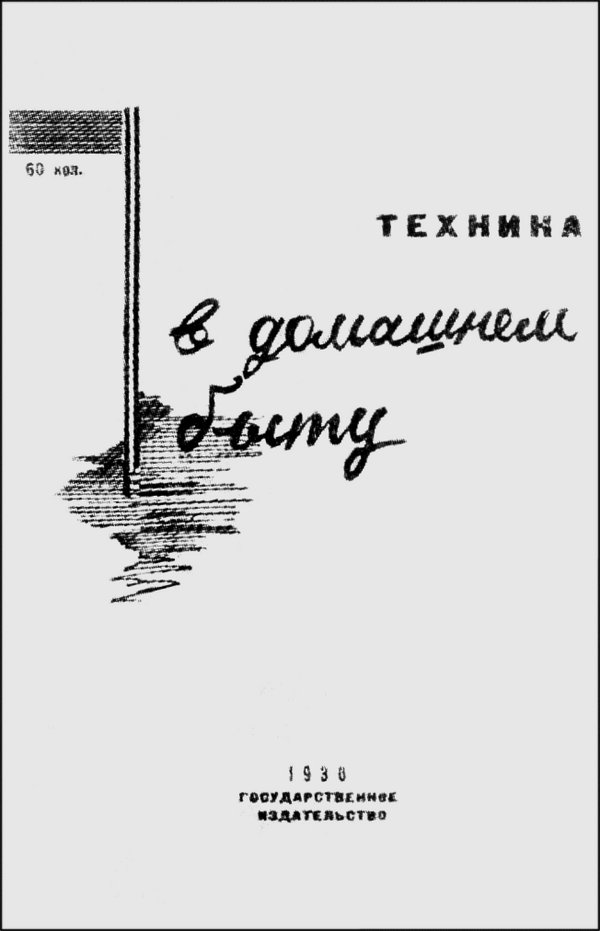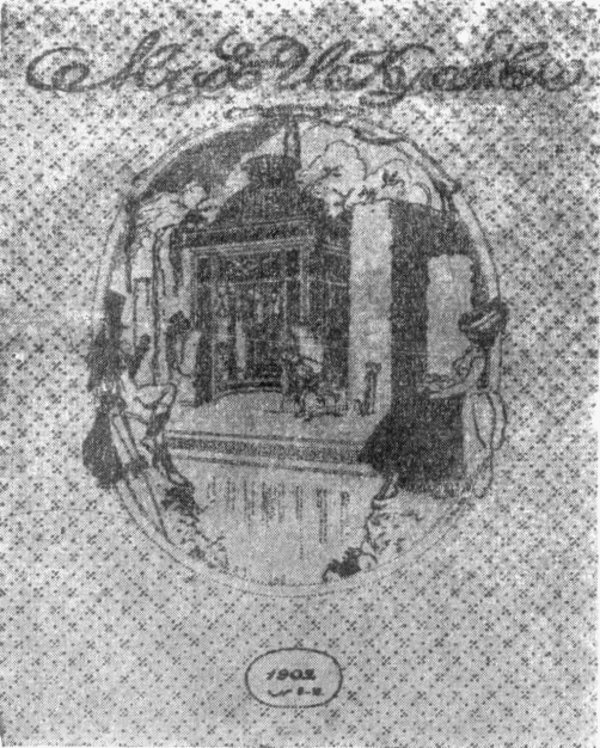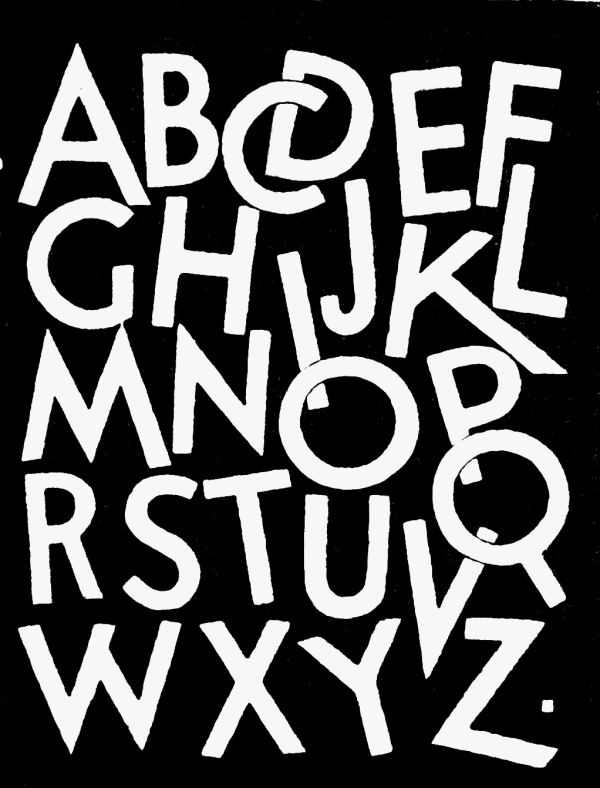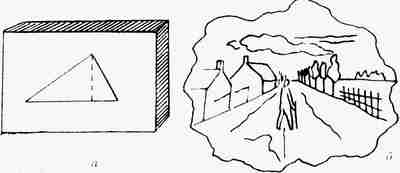
Шрифт и иллюстрация существуют рядом, на одной и той же странице, они находятся в теснейшей связи между собой, но, к сожалению; законы их взаимодействия редко принимаются во внимание. В. А. Фаворский предложил разделение всех букв на четыре группы:
Рис. 391 Разная ширина букв |
Рис. 392 "Рукописный" шрифт |
Всякая буква, взятая равномерным тонким штрихом (рис. 394, а), как бы теряет свою объемность. В буквах этого вида будет сильно сказываться движение по строке. Наиболее чистый вид такого шрифта — рукописный, особенно, если он написан карандашом. В одномерной букве основной вертикальный штрих (штамб) становится только частью контура, не отличающейся от других его частей.
Если приблизить дуги букв к полукружиям (б), усилив в то же время штамб, то этот штамб приобретает значение объемной оси, от которой зависят дуги. Буква приобретает как бы "позвоночный столб", становится предметной, объемной.
Если придать штамбу большую цветность (в), то он создаст впечатление глубины, и получится третий вид буквы — пространственный.
Крупнее: 600x931, 43kb Рис. 393 Неудачное сочетание наборного и рукописного шрифтов на обложке |
Четвертым видом буквы является жирная буква плакатного типа (г). Такая буква вследствие своей перегруженности цветом приобретает характер двухмерной цветовой поверхности.
Как бы ни относиться к предложенным условным наименованиям типов букв, следует признать, что распределение шрифтов по таким типам вполне возможно.
Из существующих типографских шрифтов к первому типу может быть отнесен рояль-гротеск (а также рукописный), ко второму — латинский, к третьему — альдине и к четвертому — дубовый.
Большая часть иллюстраций соответствует какому-нибудь одному из рассмотренных типов букв. Линейный орнамент, например, соответствует одномерной букве, предметная иллюстрация — объемной; иллюстрация пространственная, основанная на цвете и тоне, соответствует пространственной букве; четвертому типу буквы соответствует иллюстрация, выполненная в черно-белой манере.
И буквы, и иллюстрации входят одновременно в книгу и должны быть объединены. Связь между ними может быть двоякая — непосредственная и посредственная.
Если все элементы, входящие в книгу, близки между собой (например, профильные,объемные и двухмерно-цветовые), связь будет непосредственной. Если же в книгу входят разные элементы (например, профильные и пространственные), то они не могут быть объединены непосредственно, а лишь посредством подчинения одного другому или подчинения нескольких.
Рис. 394 Различные типы букв (по Фаворскому) а - одномерно-профильная; б - объемная; в - проостранственная; г - двухмерно-цветовая |
Рис. 395 Схема связи рисунка со шрифтом |
Все типы букв могут быть соединены в две группы. В одну входят буквы трофильная, объемная и двухмерно-цветовая, в другую — пространственная.
Достичь непосредственной связи между обеими группами трудно. Так, например, не всегда возможно оединение двухмерно-цветовой буквы (дубовой) с пространственной (английской или альдине).
Но и в пределах одной группы связь относительна. Она легко достижима, например, между профильной и двухмерно-цветовой буквами (рояль-гротеск и дубовый или гермес), но сложна при объединении двухмерно-цветовой с объемной.
Простейшим случаем непосредственной связи между иллюстрацией и буквой является связь предметной иллюстрации с объемной буквой. Непосредственная связь будет также между чертежом, орнаментом, плоскостной иллюстрацией, выполненной черным пятном, с одной стороны, и профильной, а также двухмерно-цветовой буквами, с другой стороны.
Один из способов объединения различных пространств — применение рамки. При помощи рамки можно трехмерную иллюстрацию подчинить двухмерной букве или, наоборот, в иллюстрацию с глубиной или объемную ввести двухмерную букву.
Мы уже говорили, что с объемной буквой легче всего объединяется предметная иллюстрация; чертеж же по своему характеру непредметен. Если бы мы пожелали соединить чертеж с объемной буквой, то можно этого достичь следующим образом: чертеж поместить на плоскость и этой плоскости дать известную толщину. Вся иллюстрация при этом получит объемность — соединится с объемной буквой (рис. 395, а).
Если бы мы захотели соединить перспективный чертеж с объемной буквой, то в этом случае может помочь виньетка в виде объемной рамы с определенной толщиной. Тем самым изображение получит предметность.
При желании соединить перспективный чертеж с профильной буквой придется поступить иначе: применить волнистую рамку (рис. 395, б). Прямоугольная рамка, которая стоит в тесной связи с принципом построения перспективного чертежа, в данном случае не могла бы помочь.
Крупнее: 600x748, 136kb Рис. 396 Обложка журнала "Мир искуства" (худ. Л. Бакст) |
Следует также помнить, что шрифт есть комбинация многих букв, образующих на страницах определенные единства, то более прозрачные, "серые", то более густые, "темные" плоскости. Иллюстративный рисунок должен учитываться также и по своему общему виду, более светлому в одном случае и более темному в другом. Контраст между этим общим "тоном" рисунка и наборной полосы невыгоден. Слишком светлый рисунок в темном шрифте кажется пятном, слишком темный в светлом наборе — дырой.
Вопрос о связи иллюстрации со шрифтом в полной мере может быть решен только художником. Однако надо уметь разбираться хотя бы в отмеченных здесь элементарных случаях. Уже одно это поможет улучшить оформление книги, особенно в титульных элементах при буквах крупных кеглей. Одновременно необходимо предостеречь оформителя книги от решения проблемы связи шрифта с иллюстрацией только с формальной стороны. Увлечение этой задачей может привести к игнорированию содержания, к превращению графического момента в самоцель, т. е. к формализму.
При иллюстрировании книги необходимо следить и за соответствием толщины штриха иллюстрации толщине основных штрихов шрифта. Насыщенные, жирные штрихи иллюстрации плохо гармонируют со шрифтом, построенным в основном на тонких штрихах. Так же плохо будет гармонировать иллюстрация, выполненная светлыми, тонкими штрихами с жирным шрифтом.
Наиболее существенным моментом при решении вопроса о художественной связи шрифта с иллюстрацией является момент стилевого единства.
Классическая иллюстрация не может быть дана рядом с вычурным, витиеватым шрифтом, и в то же время экспрессионистический рисунок вряд ли уживется рядом с четкими и строгими формами классического шрифта. Так, например, шрифт XVIII в., отразивший стиль рококо, не может быть использован для принципиальной связи с иллюстрацией, дающей образы классической Греции или Советского Союза.
Крупнее: 600x788, 36kb Рис. 397 Форзатц для букваря |
Гармоническое сочетание шрифта и иллюстрации (по их цветовой насыщенности и по их стилевым качествам) можно видеть в книгах XV — XVI вв.
В конце XIX и начале XX в. стремление придать единый стилевой характер рисунку и шрифту приводило в ряде случаев к тому, что шрифт терял свои отличительные формы, превращаясь наряду с рисунком в декоративно-орнаментальный мотив.
Это можно видеть хотя бы во многих графических произведениях группы "Мир искусства" (рис. 396).
В полиграфической практике шрифт, иногда используется в качестве рисунка с декоративными целями.
На рис. 397 дан форзац французского букваря, где алфавит, решенный декоративно, выполняет до некоторой степени учебную роль.
Декоративное использование шрифта известно еще от рукописей. Так, например, в болгарском евангелии 1356 г. симметрично повторяются на 25 строках 25 букв, дающих определенные слова. Выделенные золотом буквы образуют фигуру (крест). Декоративным узором становится шрифт в русской вязи (рис. 398).